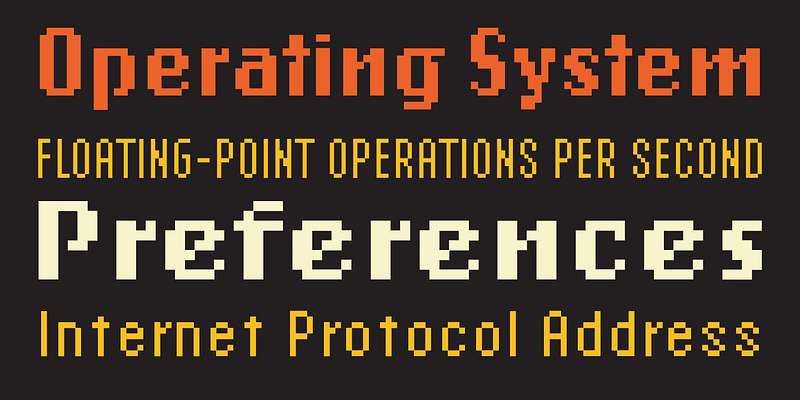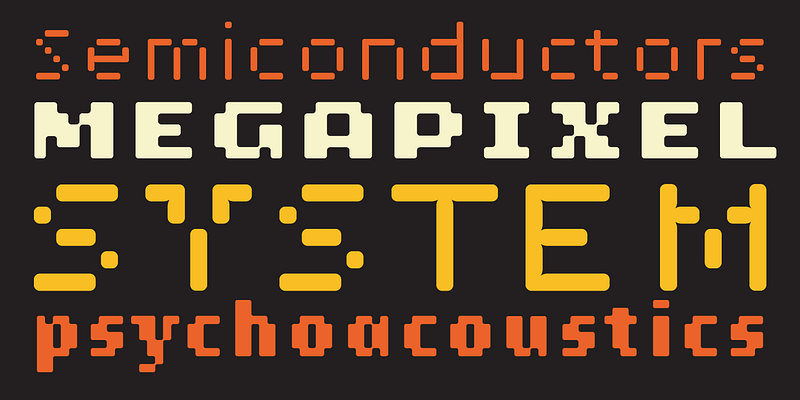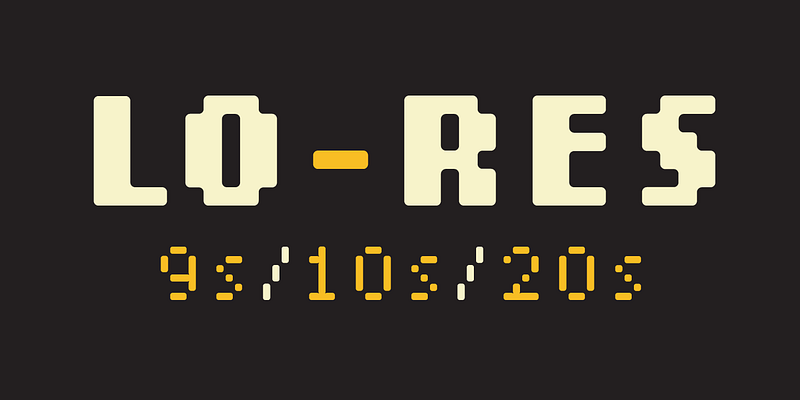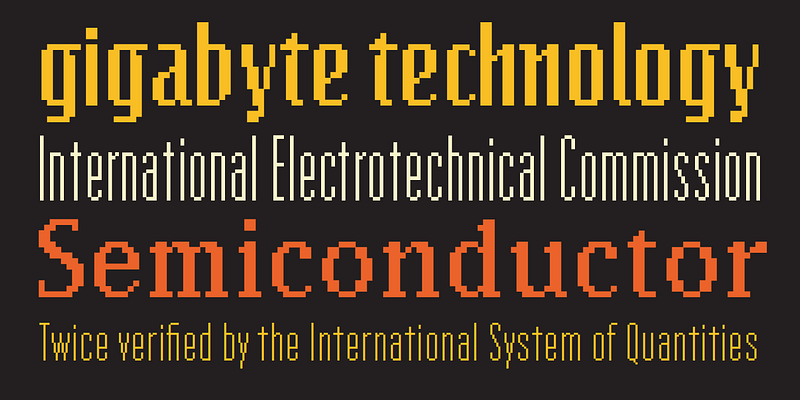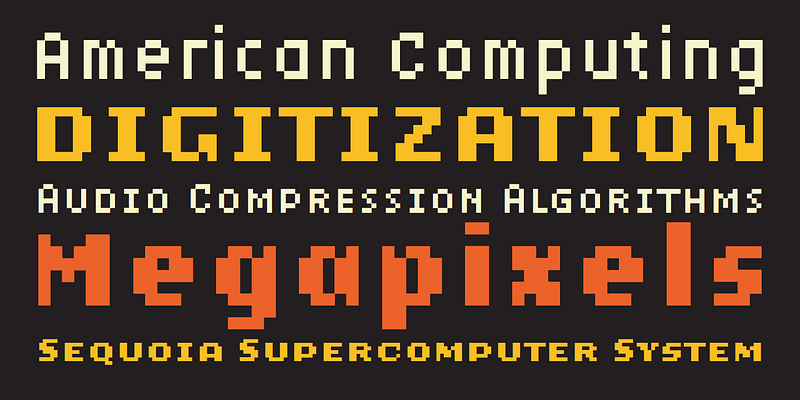
「Lo-Res」フォントファミリーは、Emigre の初期の粗い解像度のフォントや、「Base 9」のビットマップ表現などのピクセルデザインを統合したものです。従来の「Emigre」、「Emperor」、「Oakland」、「Universal」の各ファミリーに代わり、フォントメニューのファミリー名の下に関連するビットマップデザインをまとめたことで、名称や使用方法がわかりやすくなりました。「Lo-Res」フォントではまた、文字セットの充実、スタイルやウエイト間での文形の統一、さらに各解像度間のアライメントの改善など、技術的な改善も加えられています。